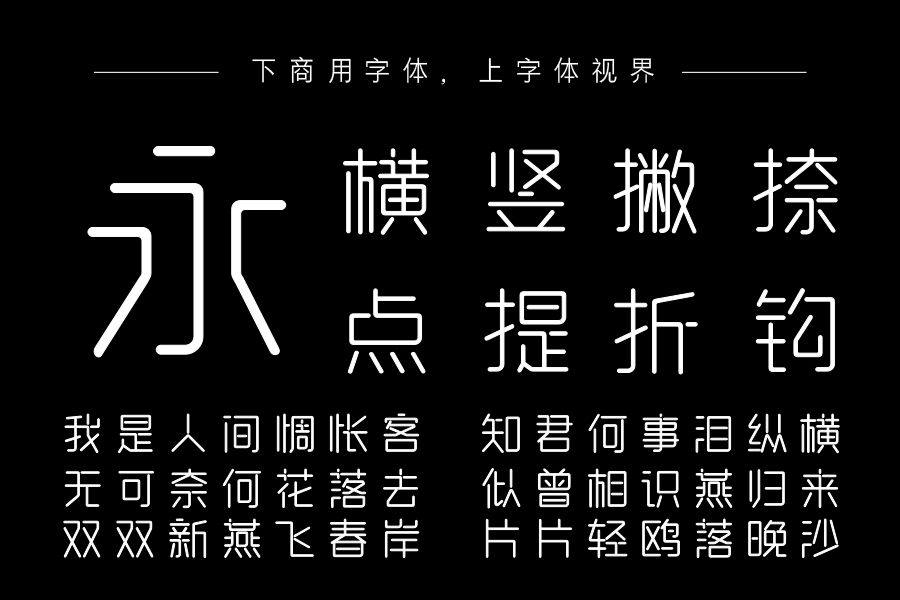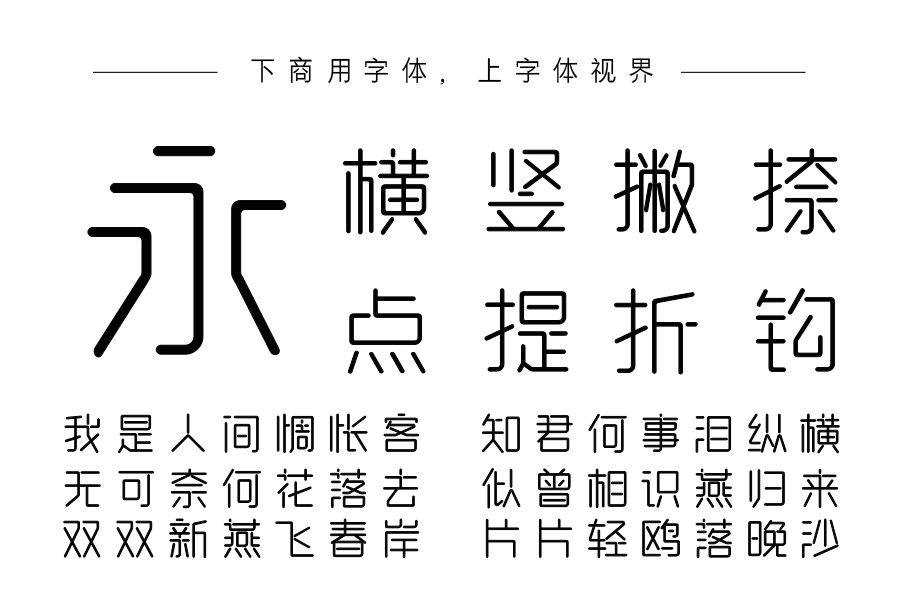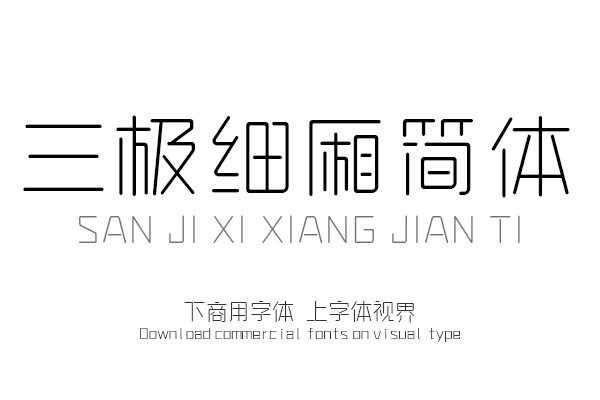
纤细的笔画设计增加了字形的易读效果,在体现笔画柔软度的同时,表现出灵动、清新气质,独特的中断空间,给使用者更加轻松愉悦的视觉感受。购买须知:“下载服务费”与“字体VIP”所获得字体 仅用于个人非商用, 商用请联系付费授权。本字体为电脑用字,手机没有root权限不支持直接手机换字(手机如何root,请自行百度搜索教程)。购买前请先 了解清楚后再付款 ,字体为虚拟产品无法回收 一旦购买不支持退款。